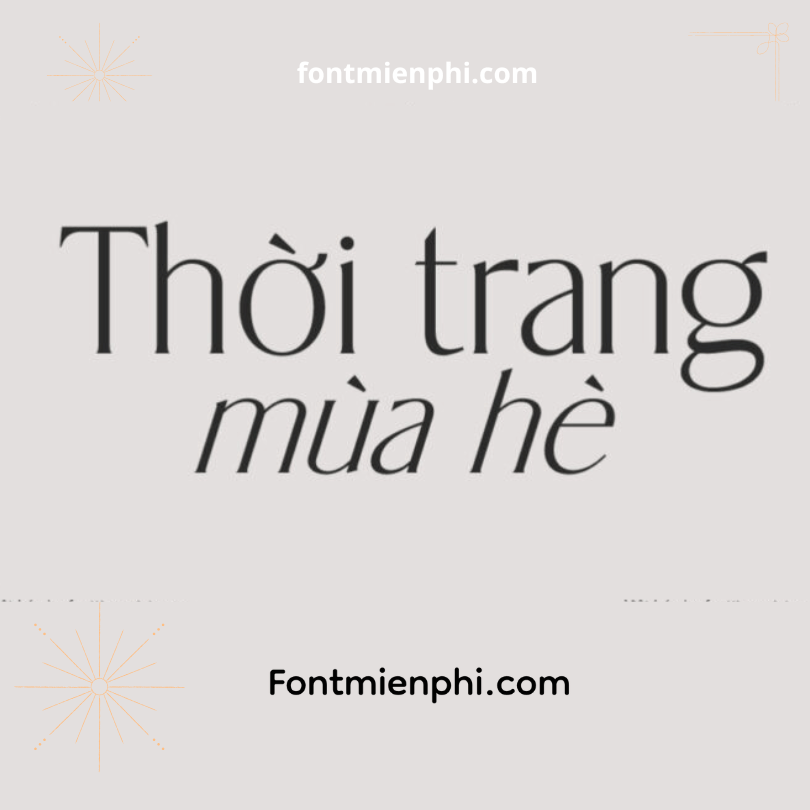
Font Việt hóa 1FTV VIP Alisheia
FONT VIỆT HÓA 1FTV VIP ALISHEIA
Kiểu chữ nghệ thuật cao cấp dành cho thiết kế đẳng cấp
1. GIỚI THIỆU
Font 1FTV VIP Alisheia là tuyệt tác typography thuộc bộ sưu tập cao cấp 1FTV, sở hữu nét chữ thanh lịch, quý phái kết hợp họa tiết nghệ thuật tinh xảo. Được Việt hóa hoàn chỉnh, font trở thành “vũ khí” không thể thiếu của designer chuyên nghiệp.
2. ĐẶC ĐIỂM CÔNG NGHỆ
✨ Bộ ký tự hoàn chỉnh:
• Hỗ trợ đầy đủ bảng mã Unicode (Tiếng Việt, Anh, ký tự đặc biệt)
Phong cách độc bản:
• Nét chữ calligraphy pha lẫn hiện đại
• Đường nét uốn lượn tinh tế, phù hợp:
• Thiệp mời cao cấp
• Logo thương hiệu sang trọng
• Packaging design
4. ỨNG DỤNG THỰC TẾ
Ngành công nghiệp sang trọng:
• Nhà hàng 5 sao – Khách sạn boutique
• Thời trang cao cấp – Mỹ phẩm luxury
Digital Content:
• Banner quảng cáo đẳng cấp
• Profile doanh nghiệp